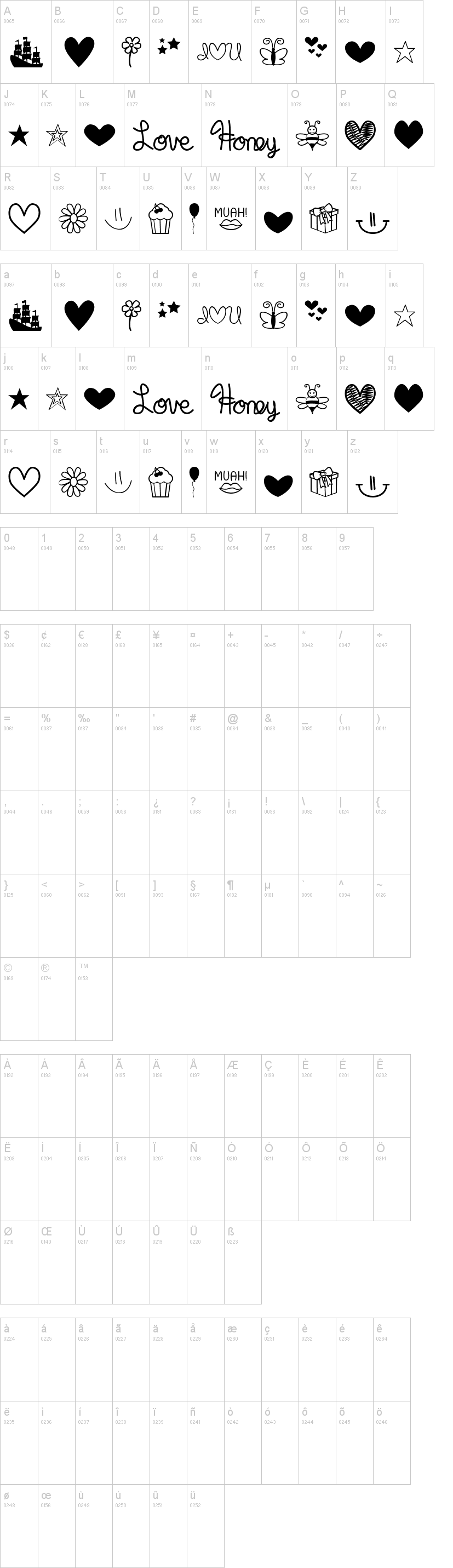
MF Dings 是一款由Monotype Imaging公司推出的字体,它是一款经典的矢量字体,可以在任何尺寸下清晰地渲染,具有良好的可读性和可访问性。它包含许多经典的符号和图形,可以用于创建各种类型的文档,如标签、标题、图表和图像。它也具有多语言支持,可以用于创建各种语言的文档,包括英语、法语、德语、西班牙语和日语等。内容介绍
MF Dings 是一款非常不错的手写艺术字体,具有很好的视觉感,适合于文化类的宣传设计、商业类品牌的广告和产品包装设计以及个性化文字排版等较多场景。